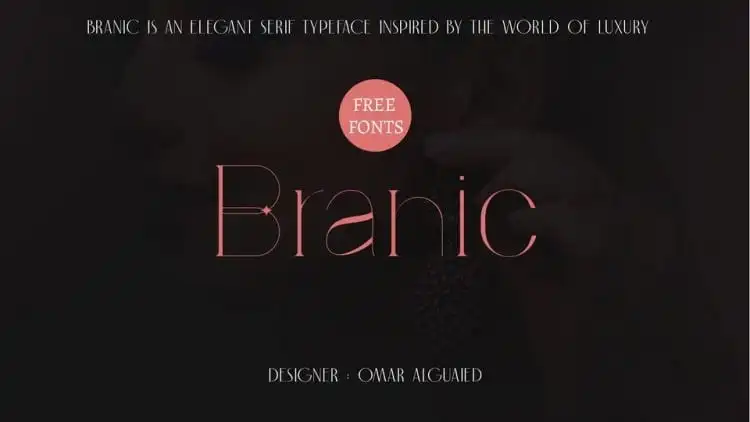
Branic Display Font
A Branic Display Font é uma elegante e moderna fonte sans serif desenvolvida pelo talentoso designer Omar Alguayyaid na plataforma 99designs. Esta fonte traz sutis detalhes que farão seu trabalho de apresentação, sua identidade visual ou até mesmo suas cartas de casamento mais sofisticadas e encantadoras. Suas linhas leves e clean são adequadas para diversas aplicações, tornando-a uma escolha perfeita não apenas para anúncios de casamento, mas também como elemento distintivo em seu próprio branding pessoal ou corporativo. O design da Branic Display oferece um equilíbrio perfeito entre simplicidade e sofisticação, garantindo que qualquer material impresso seja elegante sem perder o toque personalizado necessário para destacar sua marca ou projeto.